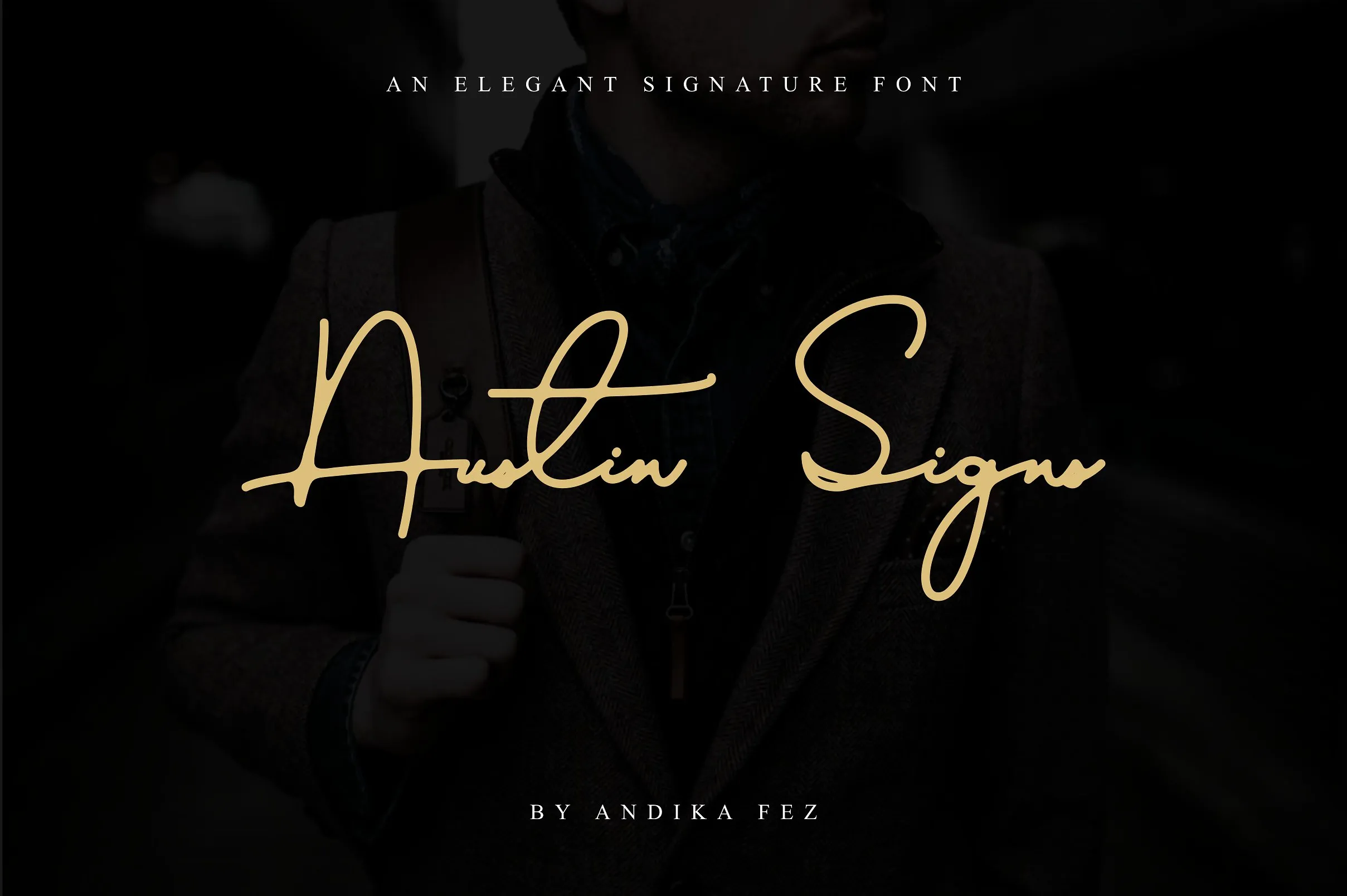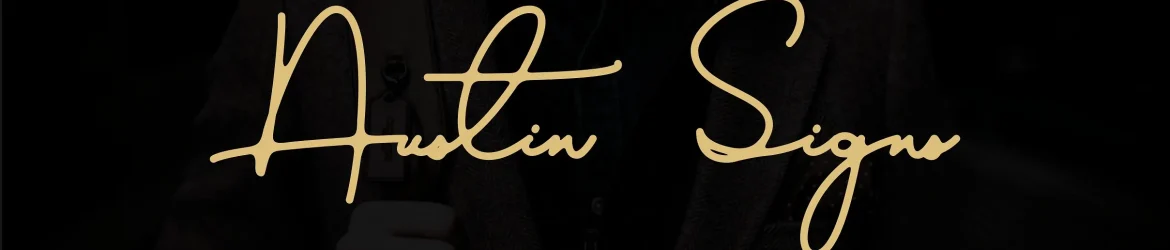
Austin Signs Font – Download Grátis
A fonte Austin Signs é uma escolha perfeita para quem busca personalidade e elegância em seus projetos criativos. Com sua característica rústica, essa fonte foi cuidadosamente desenhada para atender a diversas necessidades de design, como criação de logotipos, cardes de identidade, convites de festa, layout de revistas e necessidades de marca. Austin Signs é o tipo certo para quem procura um toque único que pode agregar valor aos seus projetos em qualquer área do design gráfico. Especialmente indicada para aqueles que buscam uma mão escrita natural, com traços achatados e espaçamento suave, esta fonte traz um ar de elegância ao seu projeto. O designer Andika Fez soube capturar a essência da escrita manual, transformando-a em uma ferramenta versátil para qualquer aplicação do design. Com Austin Signs, você não apenas economiza tempo criando logotipos e cartões de identidade, mas também adquire um toque personalizado que faz seu trabalho se destacar na multidão.
Designer: Andika Fez